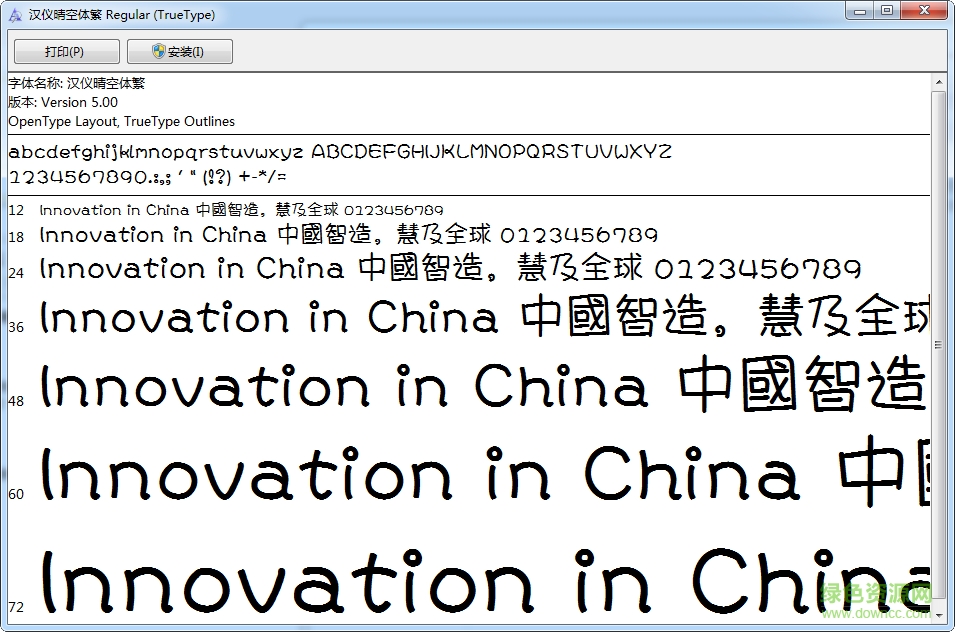
漢儀晴空體簡(jiǎn)繁字體包括了晴空體簡(jiǎn)體和繁體2款字體,漢儀晴空體是一款卡通風(fēng)格的中文藝術(shù)字體,字體輕松簡(jiǎn)單,俏皮可愛。非常有趣,適合應(yīng)用于廣告設(shè)計(jì)、POP海報(bào)設(shè)計(jì)、兒童畫冊(cè)、卡通設(shè)計(jì)等應(yīng)用。歡迎來綠色資源網(wǎng)下載。